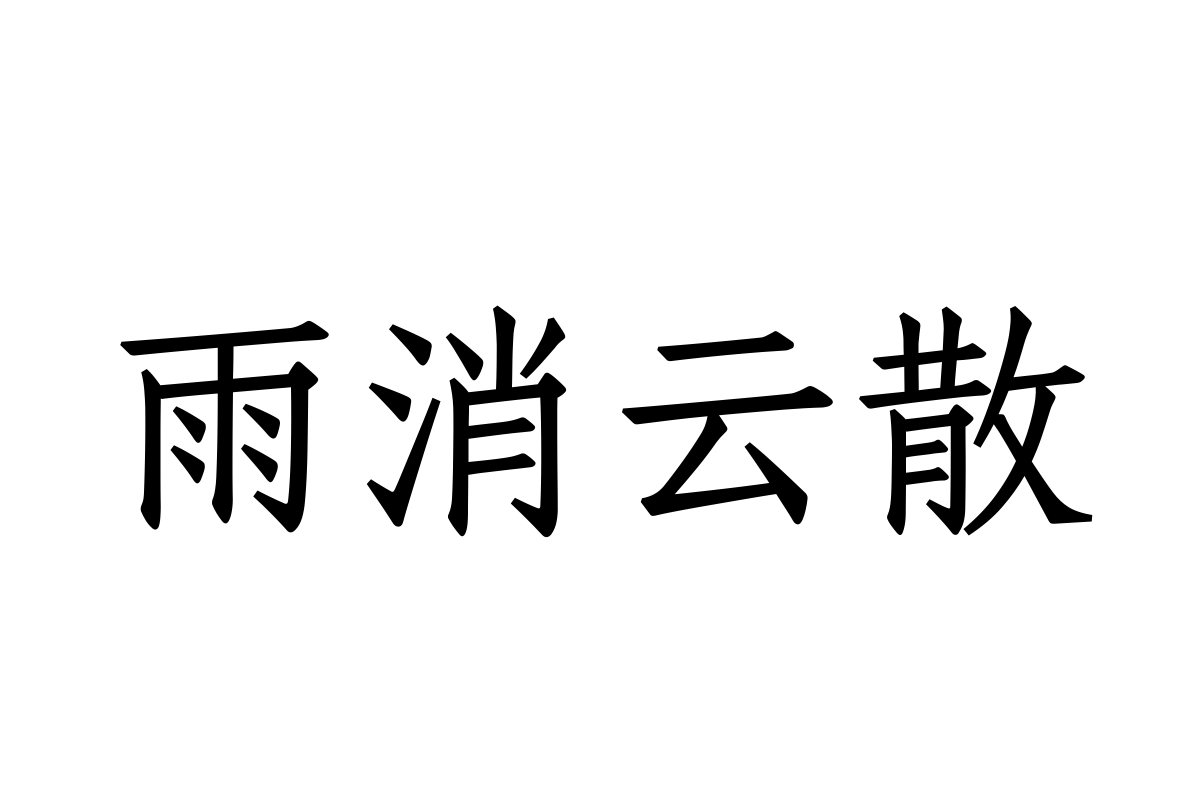
汉仪书仿55s是一款专为中文书写设计的字体,具有现代感和艺术感。它采用了简洁的线条和形状,使得书写更加流畅和自然。这款字体适用于各种书写场景,如书法、笔记、设计等。它的笔画粗细适中,既有力度又有弹性,给人一种舒适的感觉。此外,汉仪书仿55s还具有一定的装饰性,可以在书写时添加一些装饰元素,使作品更具个性和美感。总的来说,汉仪书仿55s是一款非常适合中文书写的字体,无论是初学者还是专业人士都值得尝试。